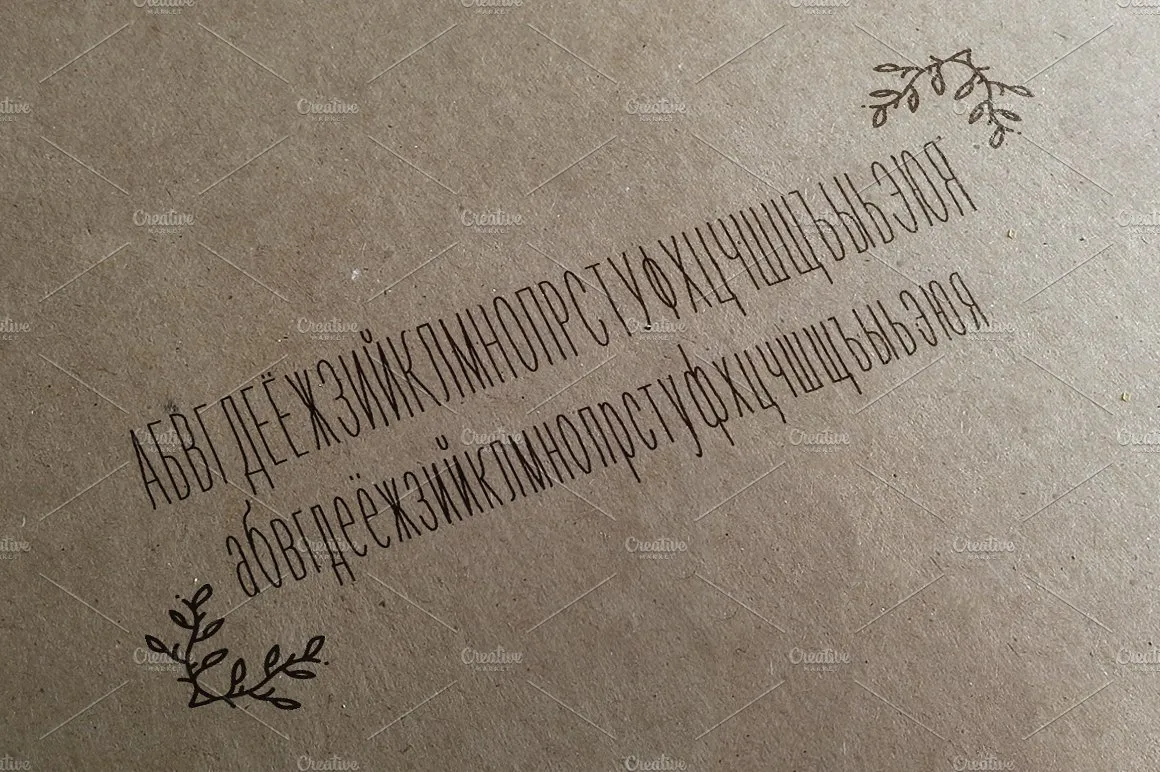
Кириллические шрифты №3
Используйте этот набор профессионально отрисованных шрифтов для оформления русского текста в презентациях, рекламных слоганах и печатной продукции. Коллекция включает гарнитуры с поддержкой кириллицы, адаптированные для работы в графических редакторах, а также тематические иконки для фуд-дизайна. Материал помогает быстро придать визуальному контенту рукописный или акцидентный стиль без необходимости создавать типографику с нуля.